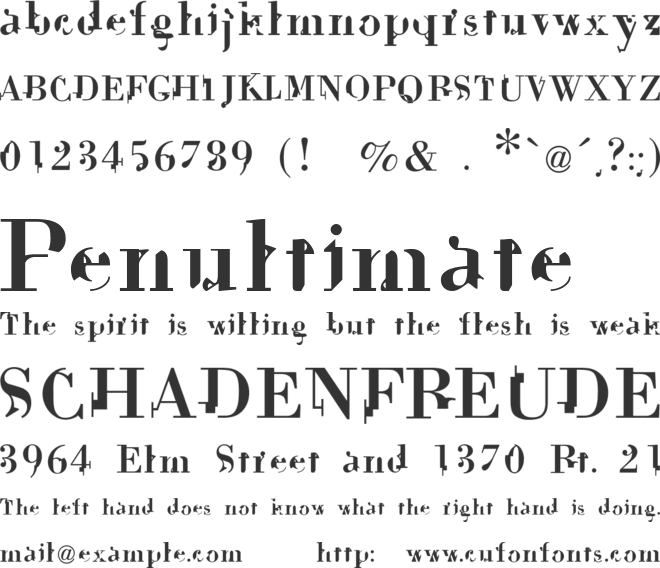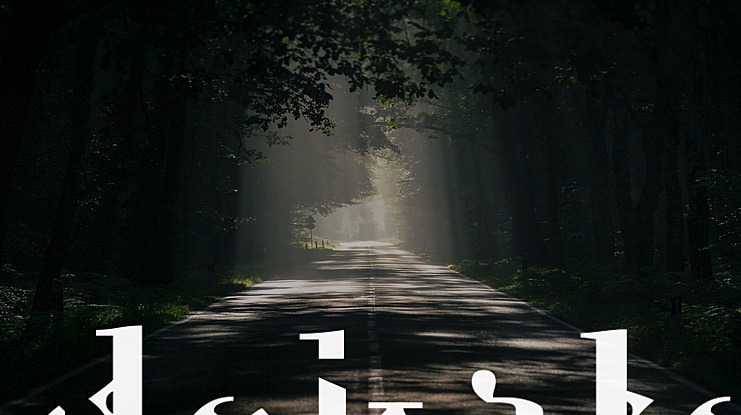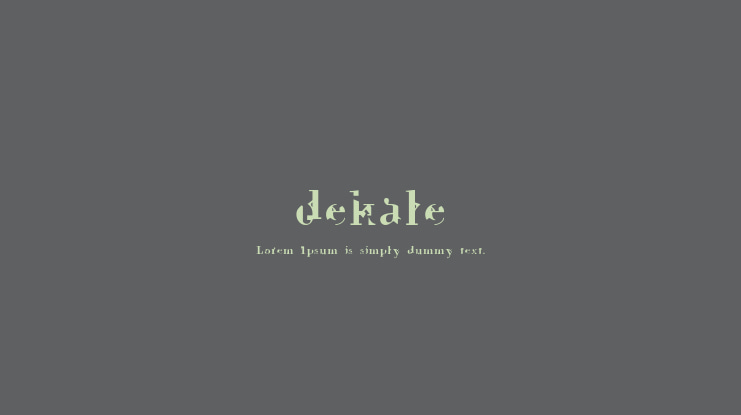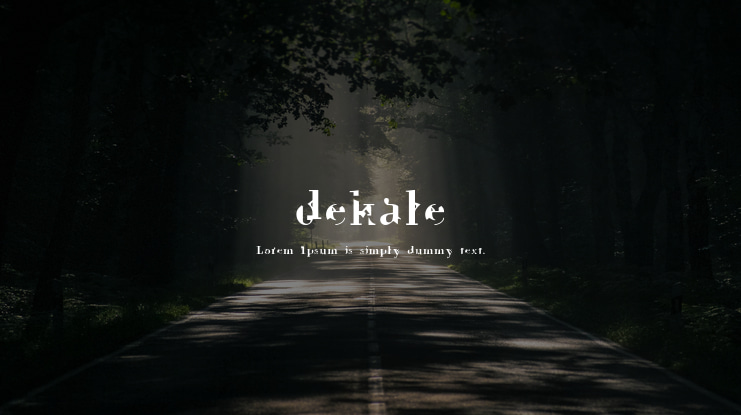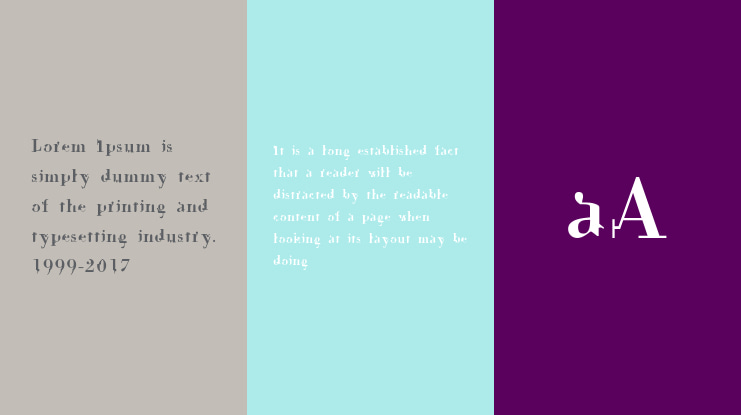
dekale Font
Jouer avec la police Bodoni en suivant la règle de chimie : rien ne se perd, rien ne se créé, tout se transforme. J'ai appliquer cela à presque chaque glyphe. Les lettres ont un aspect destructuré tout en conservant leur lisibilité.